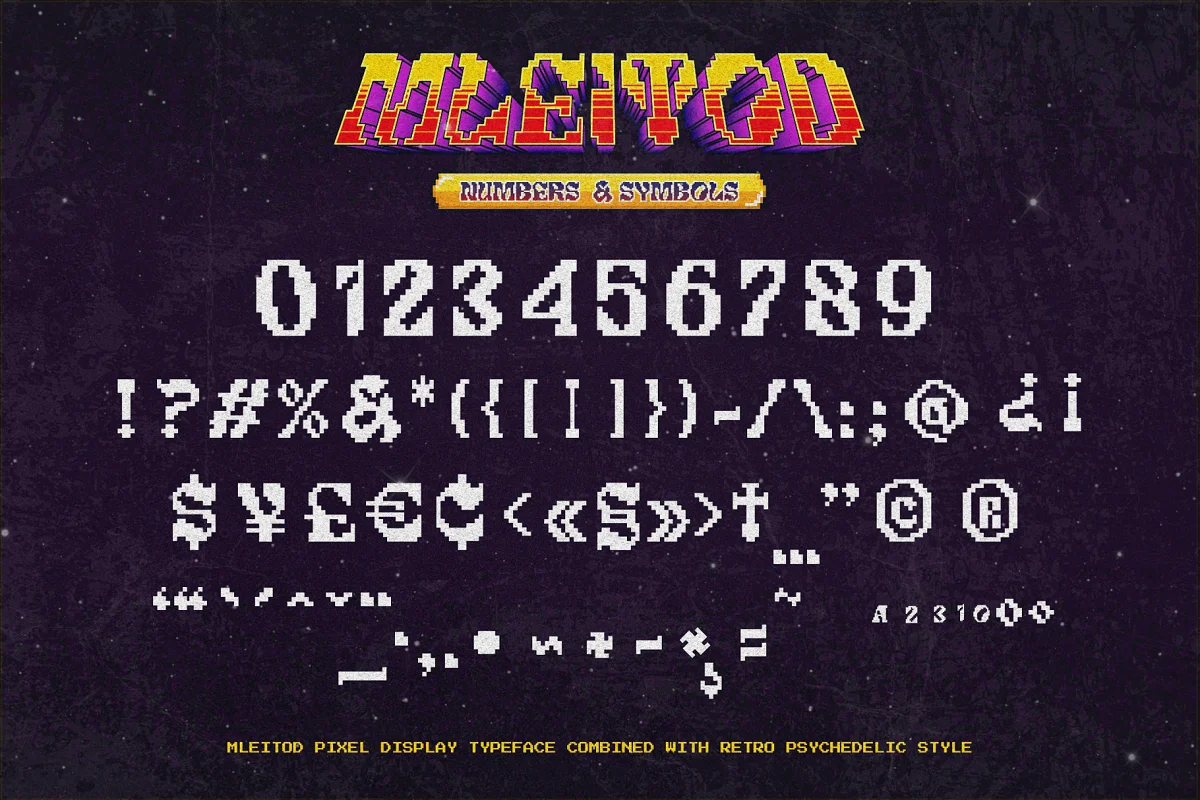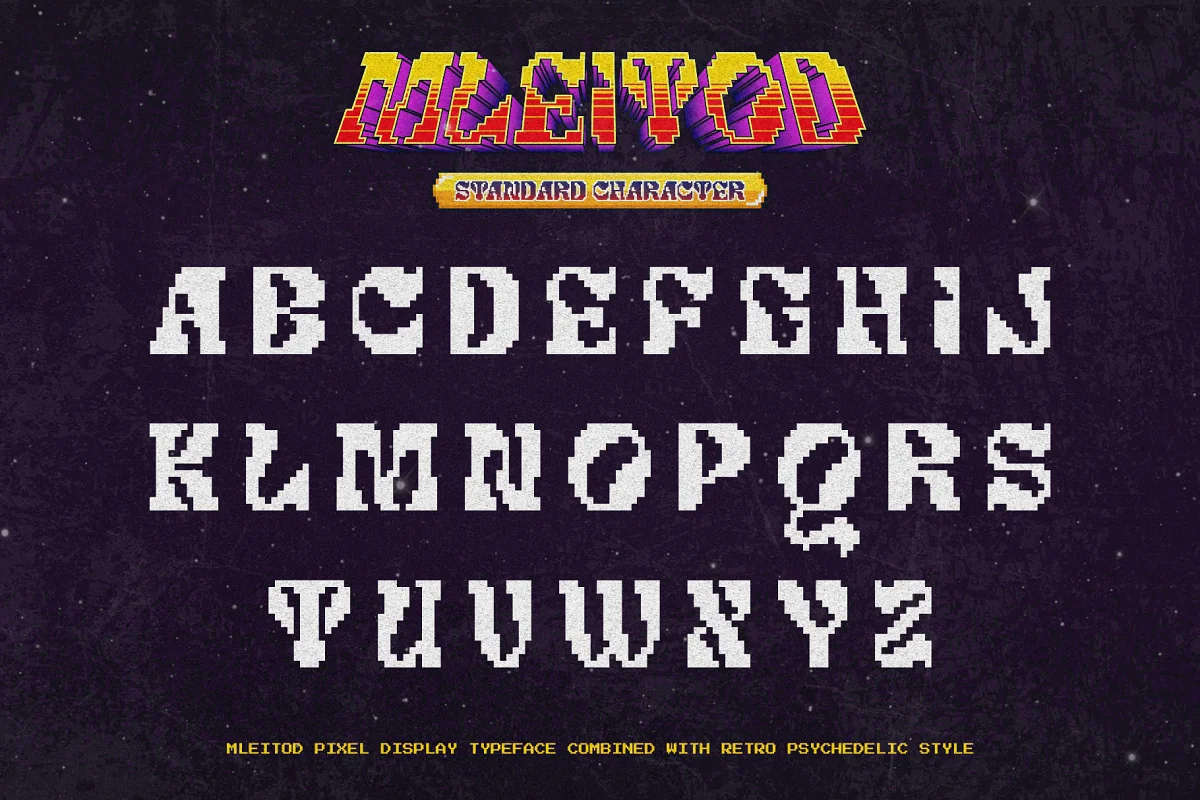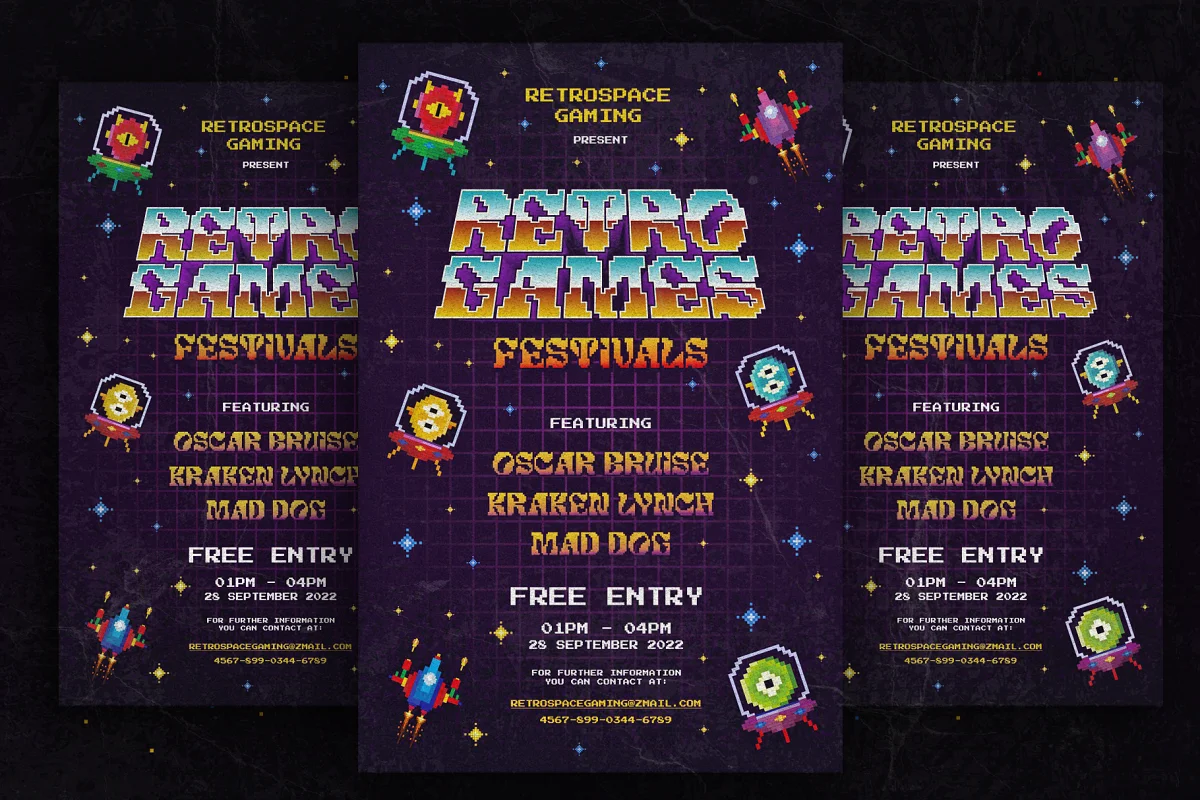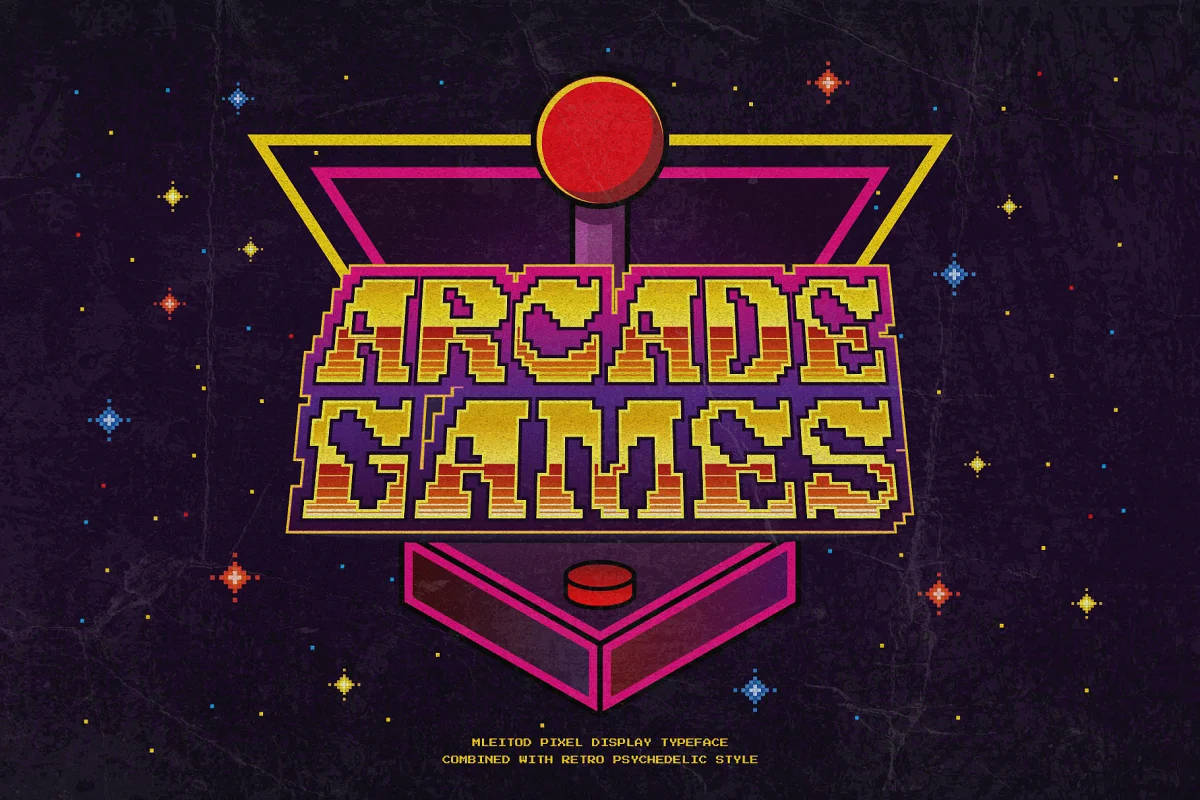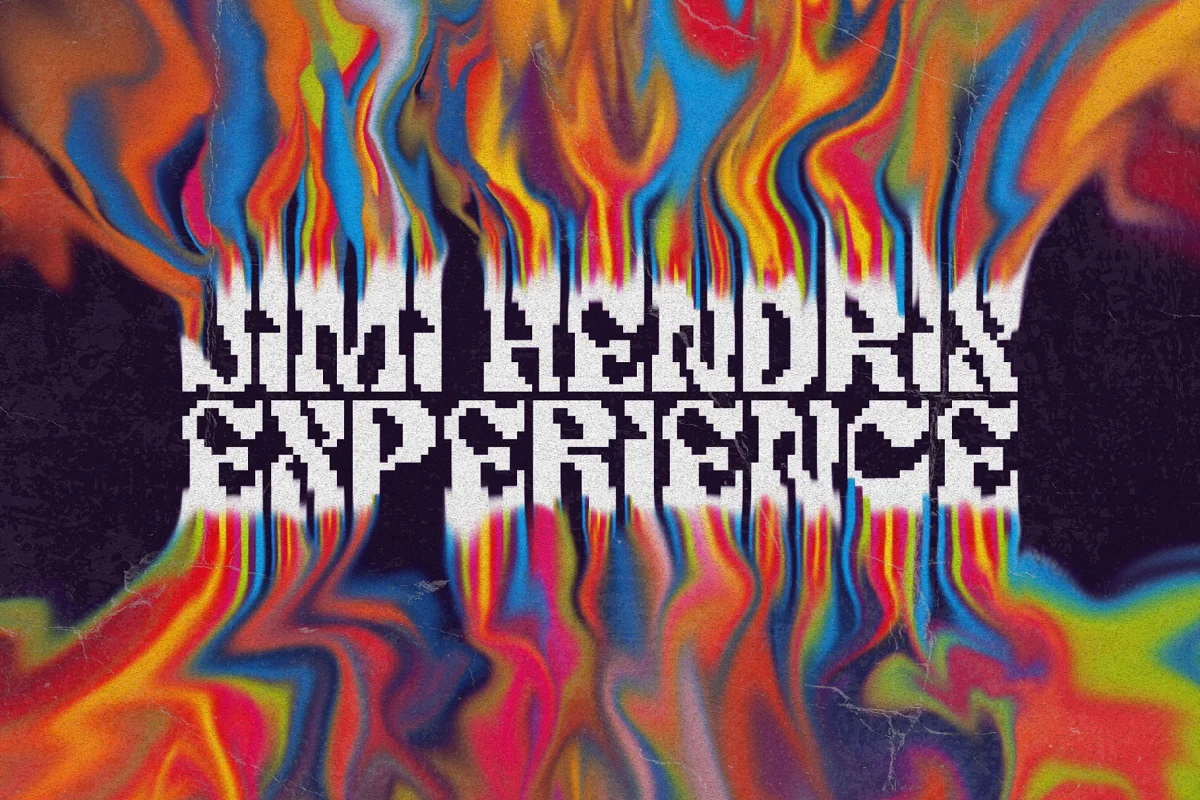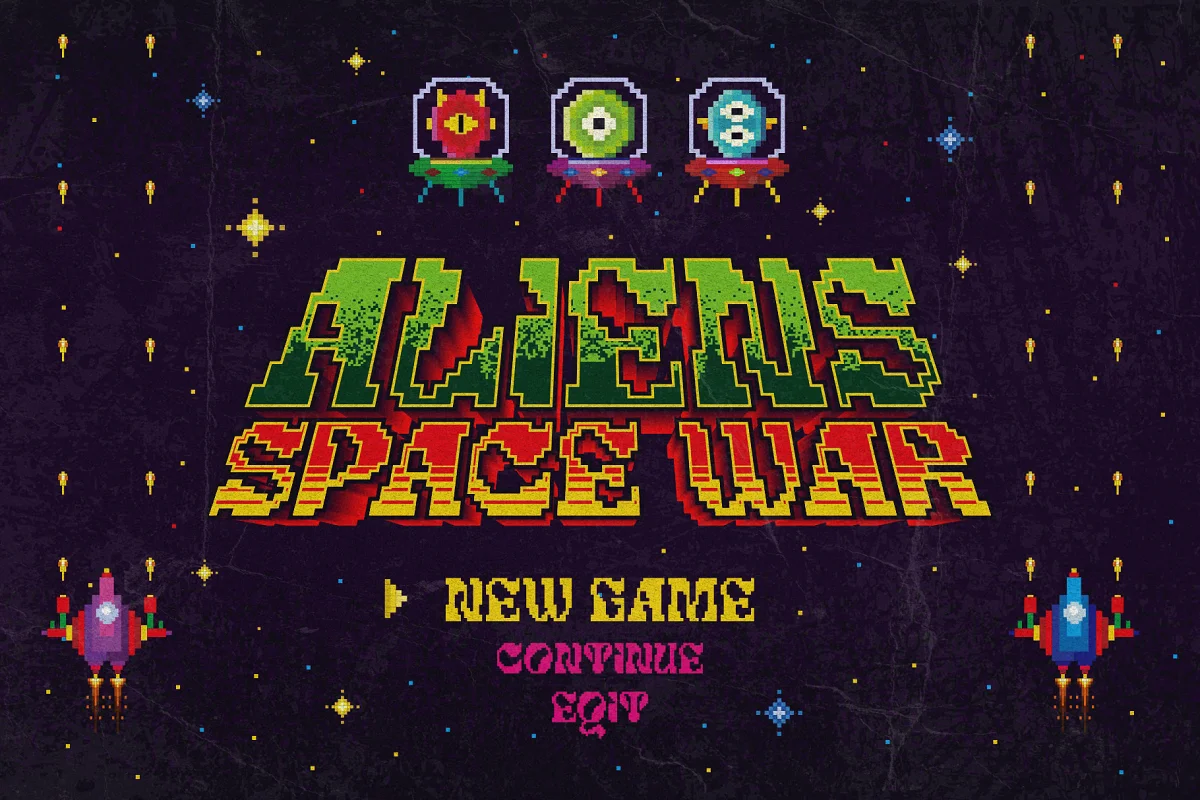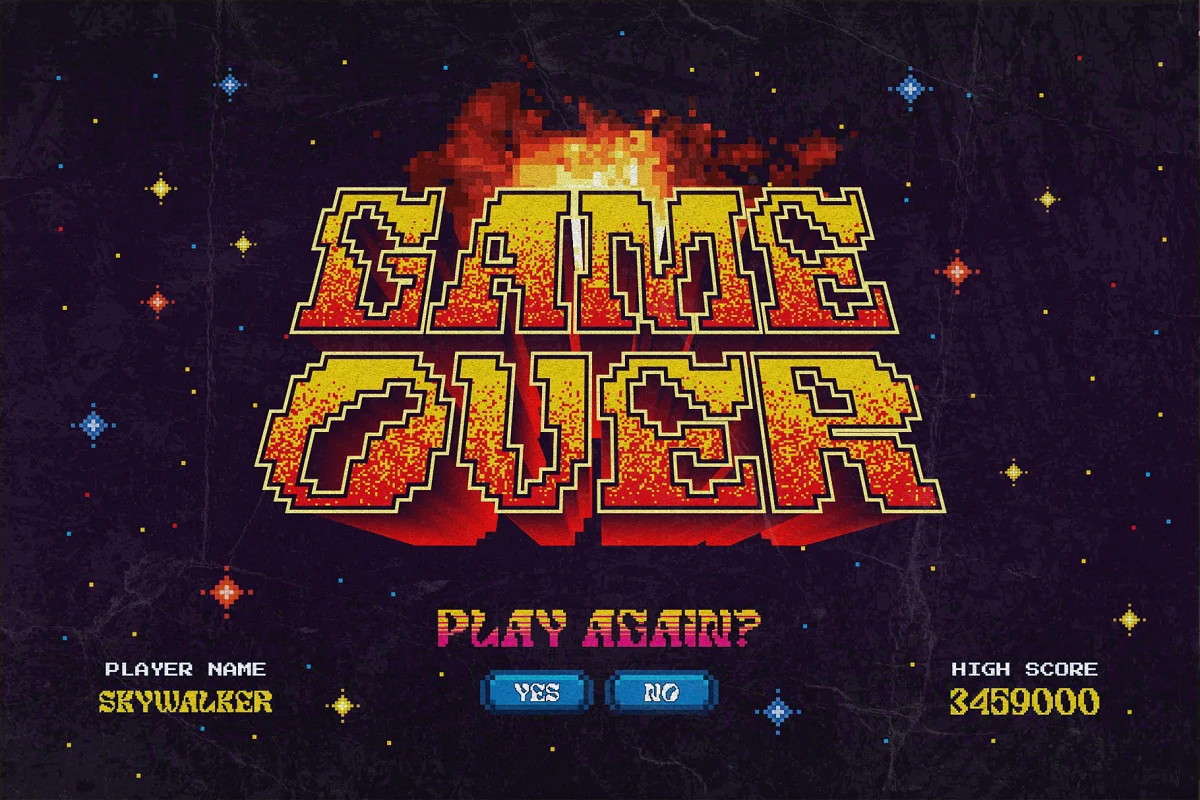
MLEITOD
Mleitod là một phông chữ hiển thị dựa trên các chữ serif đậm kết hợp với phong cách ảo giác và mang lại hiệu ứng pixel thấp giống như trong trò chơi. Với đặc điểm nét vẽ pixel, phông chữ này hoàn hảo cho các thiết kế khác biệt hoặc độc đáo, chẳng hạn như trong trò chơi hoặc cho các ban nhạc và áp phích sự kiện âm nhạc.
Điểm độc đáo của phông chữ này là pixel ảo giác, nó có thể được phân loại là phông chữ cổ điển vì thông thường các trò chơi trường học cũ sử dụng phong cách này và nó có thể được sử dụng cho các ban nhạc vì ảo giác cũng được tìm thấy trong một thể loại âm nhạc.